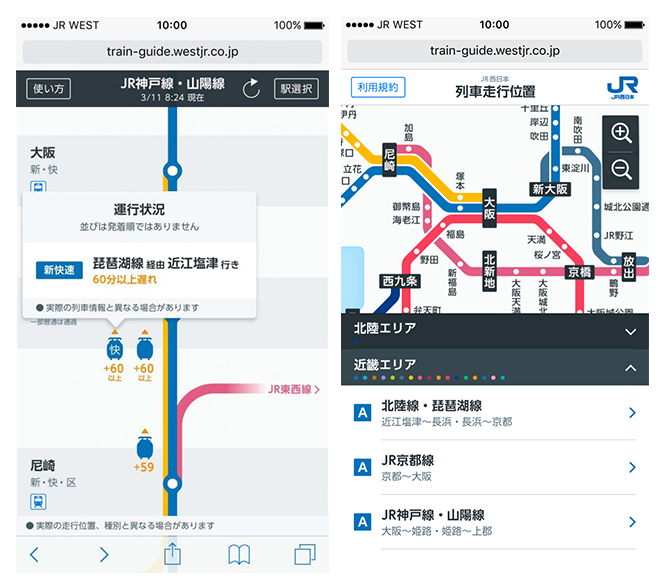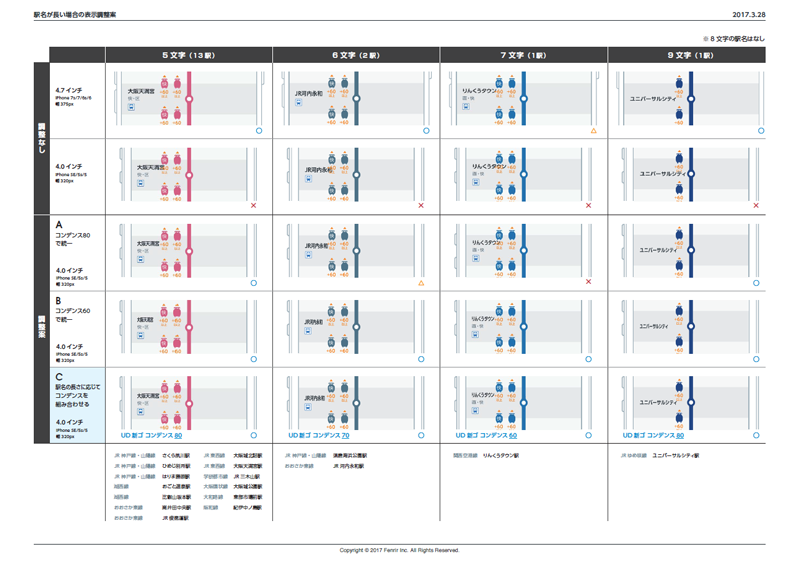
デザインの最前線で選ばれる
Morisawa Fontsシームレスな移行と
広がるフォント活用の可能性
スマートフォンアプリ、Webアプリの開発と自社プロダクトの開発を主に、UXやUIデザインを手掛けるフェンリル株式会社(以下、フェンリル)。常にユーザー目線を意識しているというアプリの開発実績は600を超え、中には月間700万PVや100万ダウンロードを獲得したものもあるという。こうしたアプリ開発や自社広報物など、さまざまな場面でモリサワのフォントを活用している。
今回、MORISAWA PASSPORTから後継サービスであるMorisawa Fontsへ移行したフェンリルのディレクター3名に、Morisawa Fontsの印象や導入後の変化、そしてフォントの選び方について話を伺った。
活用シーンの増加と思いがけない変化
一方、社内外のイベントやノベルティ、自社プロダクトのグッズなどブランディングに関する幅広い広報物等を制作するブランディング部。ここでは、Morisawa Fontsの各種機能を業務に活用し始めている。まず一つは、選択したフォントに好きな文章を当てはめ、即時表示できる「プレビュー機能」。広報物はシンプルに文字のみで制作するものも多く、デザインの一部としてフォントが担う役割は大きい。そのため、フォント選びは慎重に、丁寧に行うことが常である。近年増加したオンラインミーティングの場では、Morisawa Fontsのプレビュー画面を共有することでフォント選定のディスカッションがスピーディに進み、候補として選んだフォントをプレビュー画面上でアクティベートすることが可能に。ワンクリックで広報物へ反映できるため、全体の業務効率もアップしたそうだ。
そして二つ目は、利用するフォントをプロジェクト毎にグループ化できる「コレクション機能」だ。例えばメッセージ性の強い広報物にはヒューマニスティックな明朝体、情報を的確に伝達したい広報物には視認性の高いゴシック体といったように、発信する内容によってフォントを変えることは多い。しかし同じ明朝体であっても、プロジェクトの中で異なるフォントファミリーの明朝体が混在すると、受け手の印象は変わってしまう。
ブランディング部デザイナーの児玉氏が「発信のたびに使用フォントが微妙に異なると、その印象のブレが企業イメージのブレにつながる可能性があります」と説明するように、フォントを統一することはブランディングの一つなのだ。現在は広報物に使用する固定フォントをコレクションに登録。プロジェクトへ新たに関わるメンバーや普段デザイン業務に携わっていないメンバーへのスムーズな情報共有に繋がり、ブレの発生する懸念が払拭されたと話す。
業務での活用機会が増えるうちに、バックオフィスを中心とした非デザイナーたちの行動や気持ちにも変化が波及。「フォントはデザイナーだけのものではない、フォントは面白いと思ってもらえたんじゃないでしょうか」と児玉氏。Morisawa Fontsの使用でフォント選びのハードルが下がった。そのため、非デザイナーが積極的に使用するフォントの提案をしたり、ライセンスを持たないバックオフィス担当者からMorisawa Fontsの導入を検討したりする声が届いているそう。「フォントがもっと身近な存在になった」と、うれしい声が聞こえてきた。
モリサワのフォントを選ぶ理由が、また一つ増えた
フェンリルでは、アプリやWebサイトの開発において、実にさまざまなシーンでモリサワのフォントを使用している。今回紹介してくれたのは、西日本旅客鉄道株式会社(以下、JR西日本)の列車運行情報をリアルタイムに提供するWebアプリ「JR西日本 列車走行位置」。
メインで使用しているフォントは「UD新ゴ」。実際の駅名標で使われている「新ゴ」に合わせて選定したものだが、駅名の文字数に合わせてコンデンス書体※も活用している。
※コンデンス書体:基準となる書体に比べて、横幅が狭く設計されている書体。横幅を狭くしつつも、視認性・可読性を損なうことなく表示できるようにデザインされている。
スマートフォンの小さな画面でも視認性と可読性を保ち、誤認識や誤案内が防げるように、コンデンス書体の提案、及びユーザーが見慣れている駅名標のフォントをベースとしたユニバーサルデザイン書体を使うことで、JR西日本らしいデザインにすることをフェンリルから提案したという。
フォントの選定基準を中西氏に尋ねたところ、目的や要件にかない文脈に沿うフォントであることを前提として、以下の多角的な視点を教えてくれた。
①書体の由来、文字の表情、本文を組んだ時の印象などの意味性・情緒性
②ユニバーサルデザイン、コンデンス書体、ペアカーニングなどの機能性
③デバイスフォント※だから誰でも使える、ウェイトが豊富で欧文と混植しやすいなどの利便性
モバイルアプリやWebサイト、そして紙媒体など、フォントを使用したデザインのアウトプット先が多様を極める現代では、より簡単に、より安全にフォントを使える有益性は計り知れない。“デザインと技術”をキーワードに、デザインの最前線で活躍するフェンリルにおいて、Morisawa Fontsが新たな可能性を生む存在となっている。